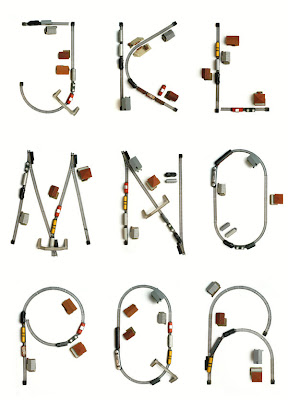
"Tipografía tren de juguete" de Ludvig Bruneau Rossow, es el artista de este impresionante trabajo creado con un tren de juguete que su abuelita aun conservaba en el sótano, con el cual ha logrado armar una tipografía con un estilo de trazo singular y diferente al de muchas otras fuentes con estructuras similares, nos introduce Ludvig Bruneau Rossow en este contexto de tipografía y diversión, donde el circulo es una figura presente en la elaboración de cada trazo presente en cada letra, aunque apenas es un principiante, ya es capaz de experimentar con diversas formas, en este caso juguetes en los que la adecuación de cada letra no solo rompen con lo tradicional, sino que refuerzan el punto de atención de los observadores